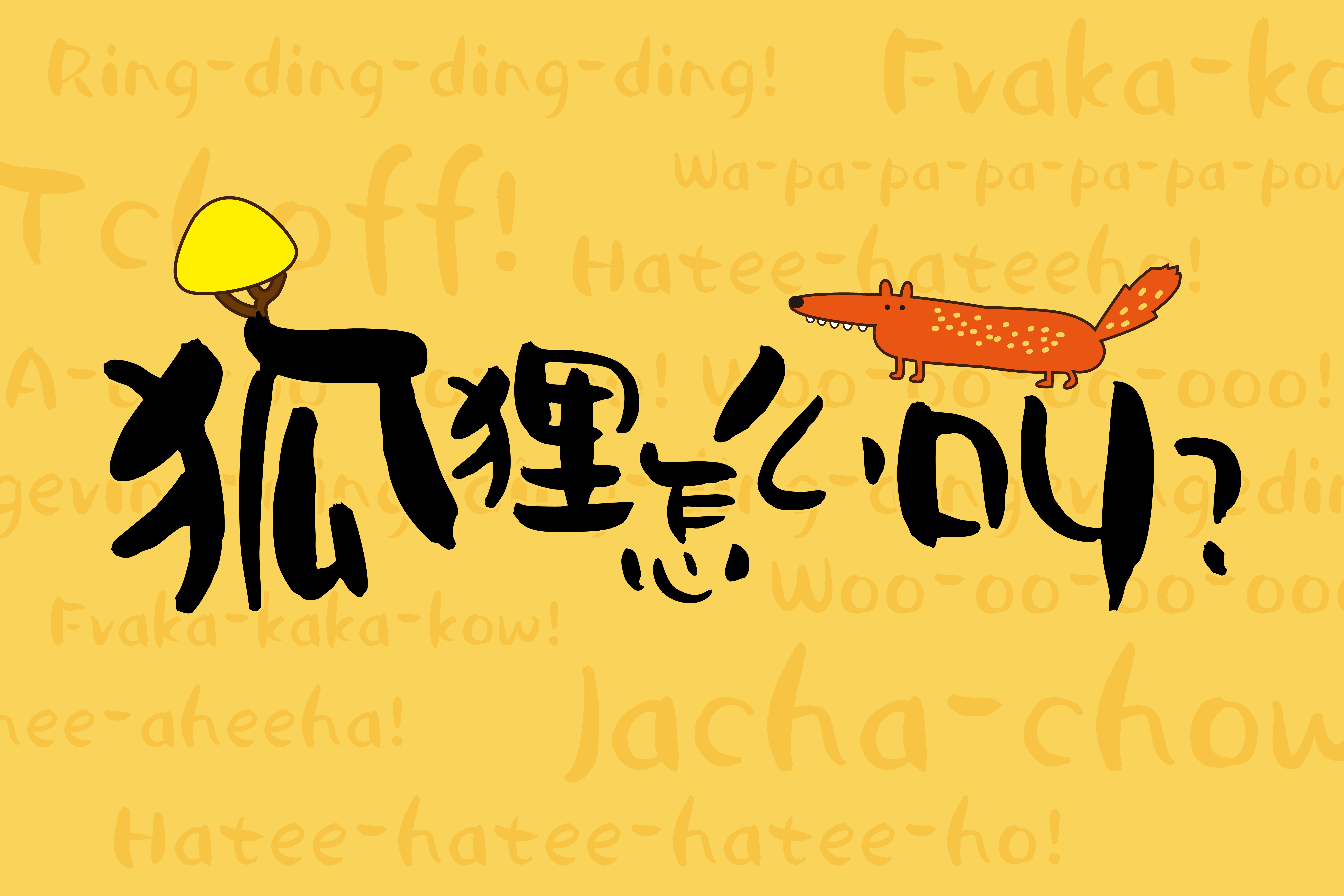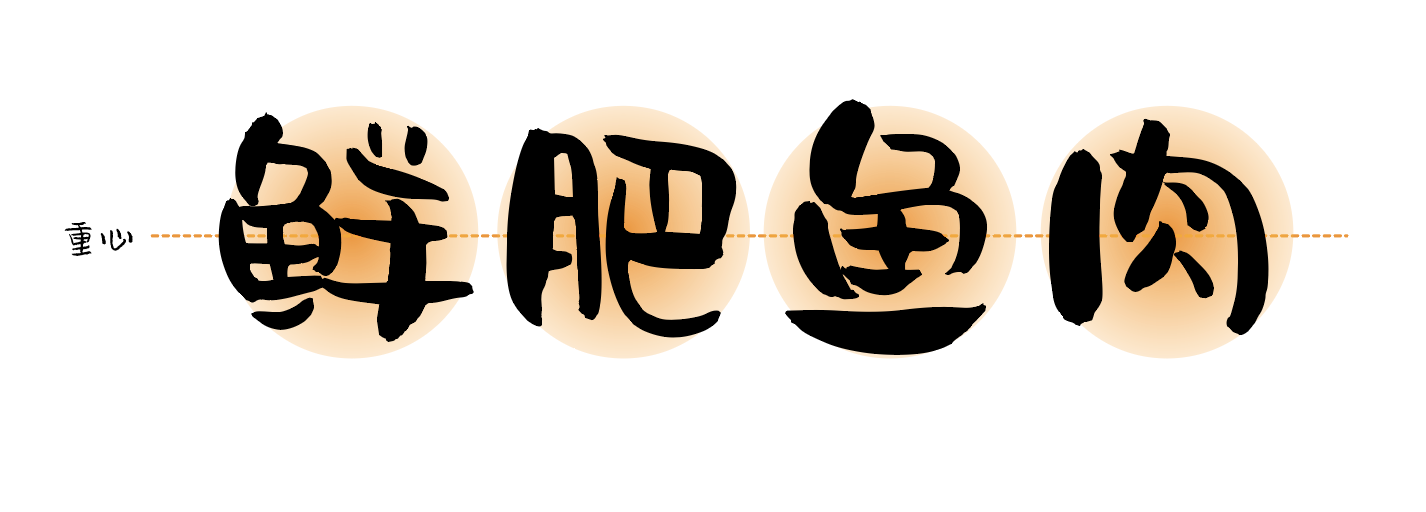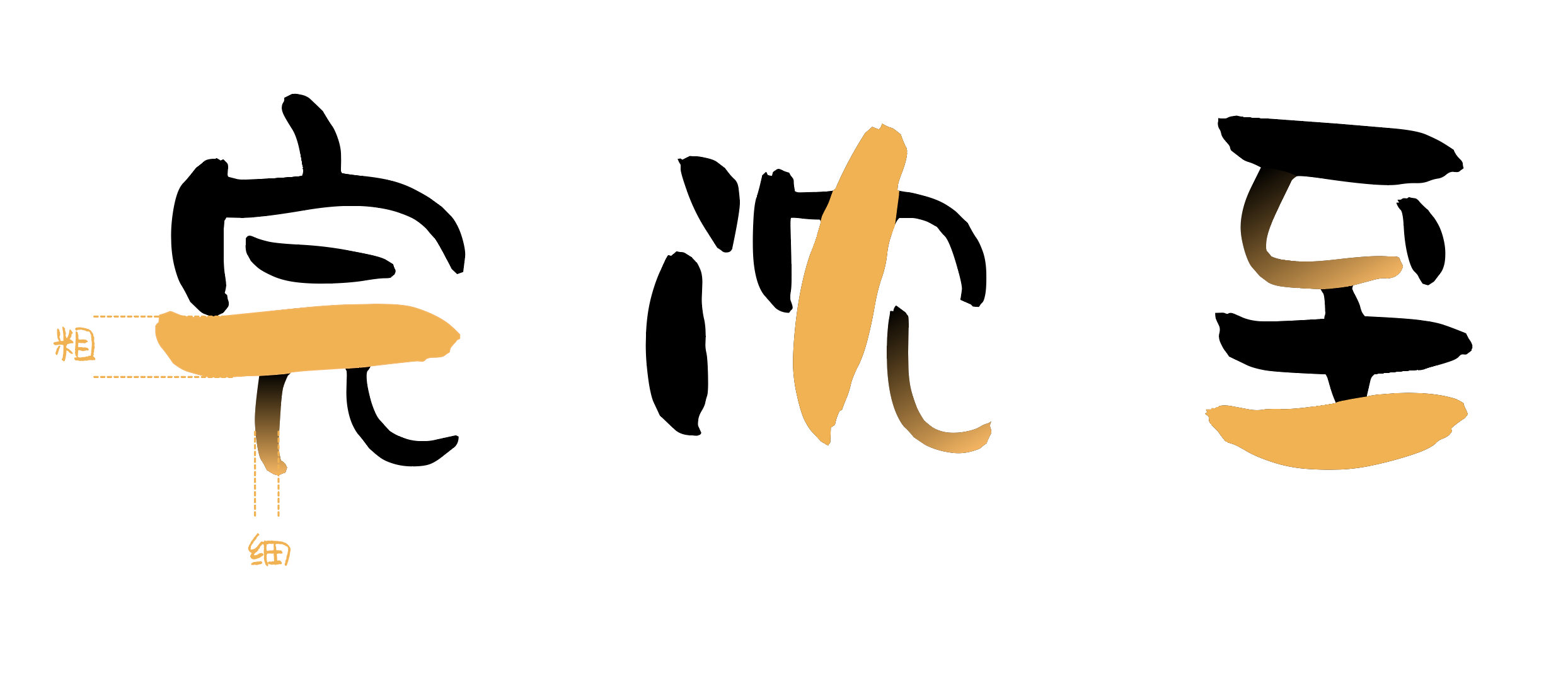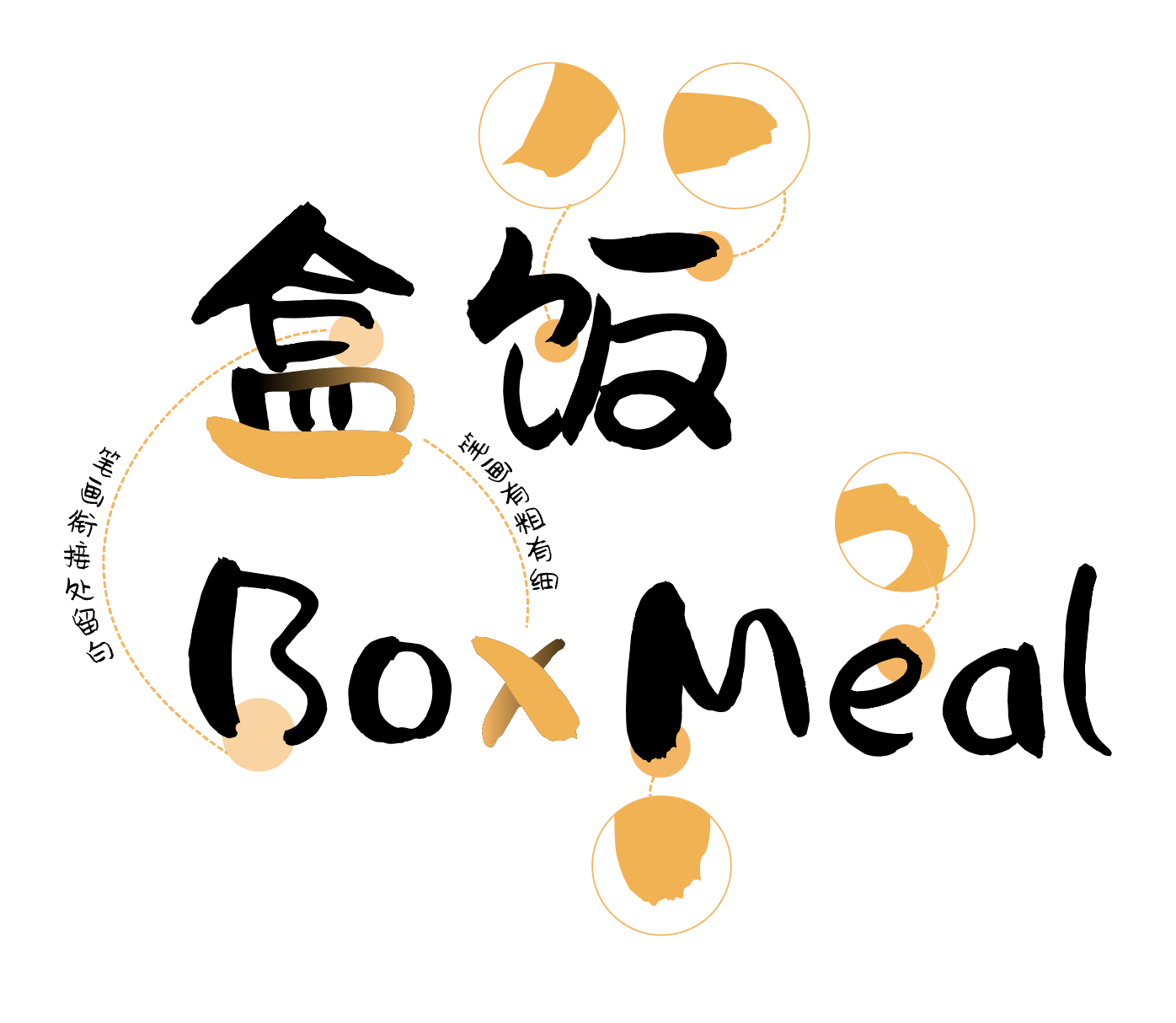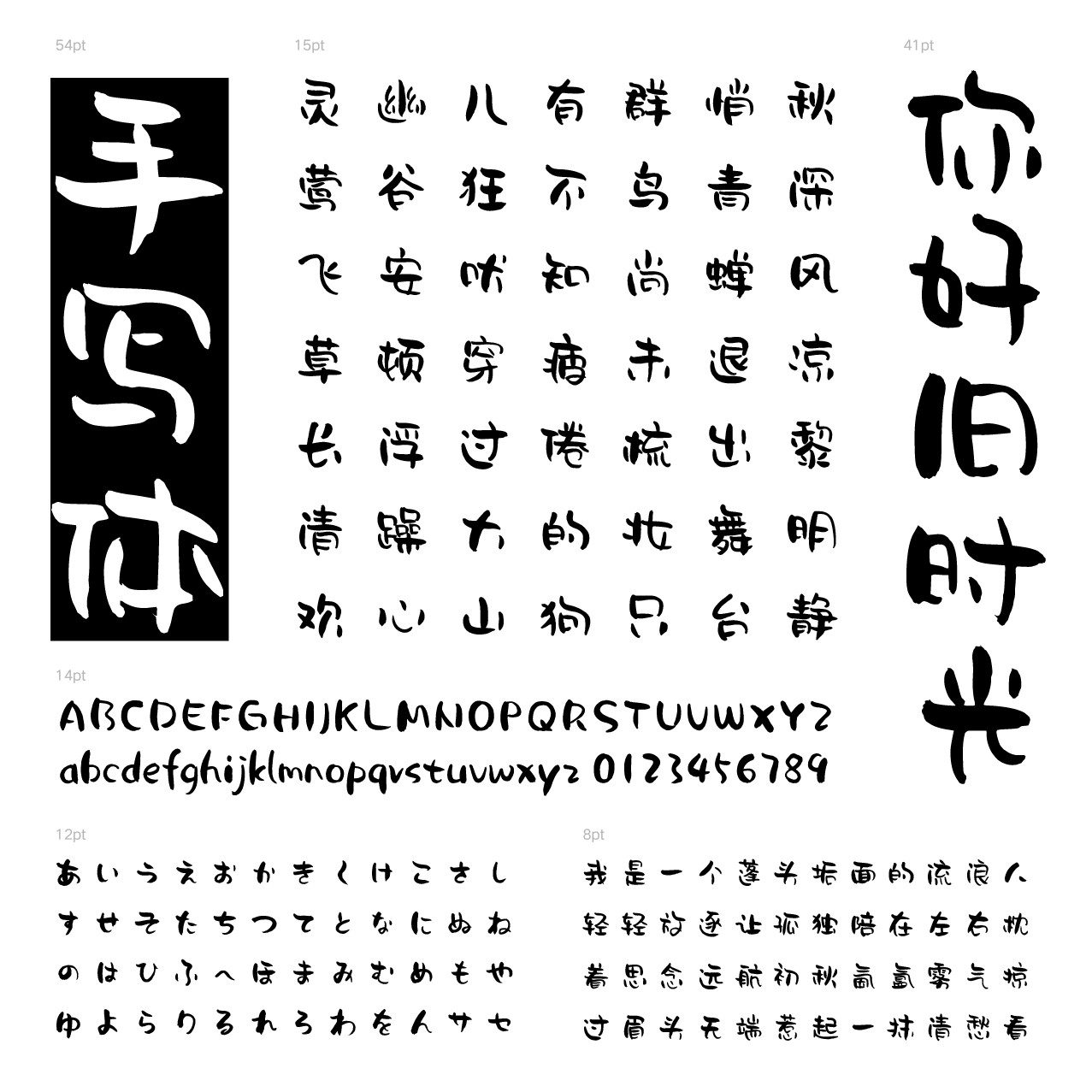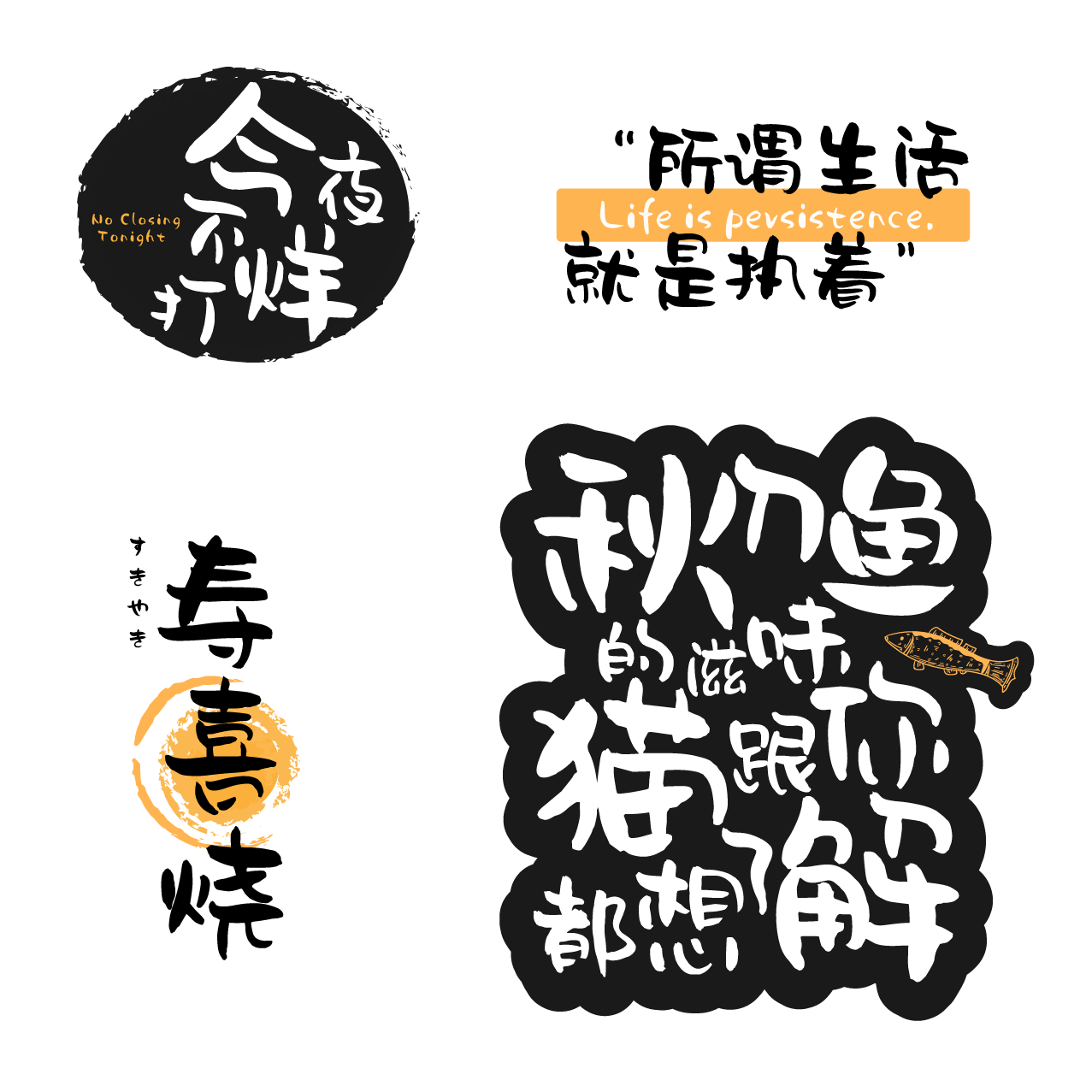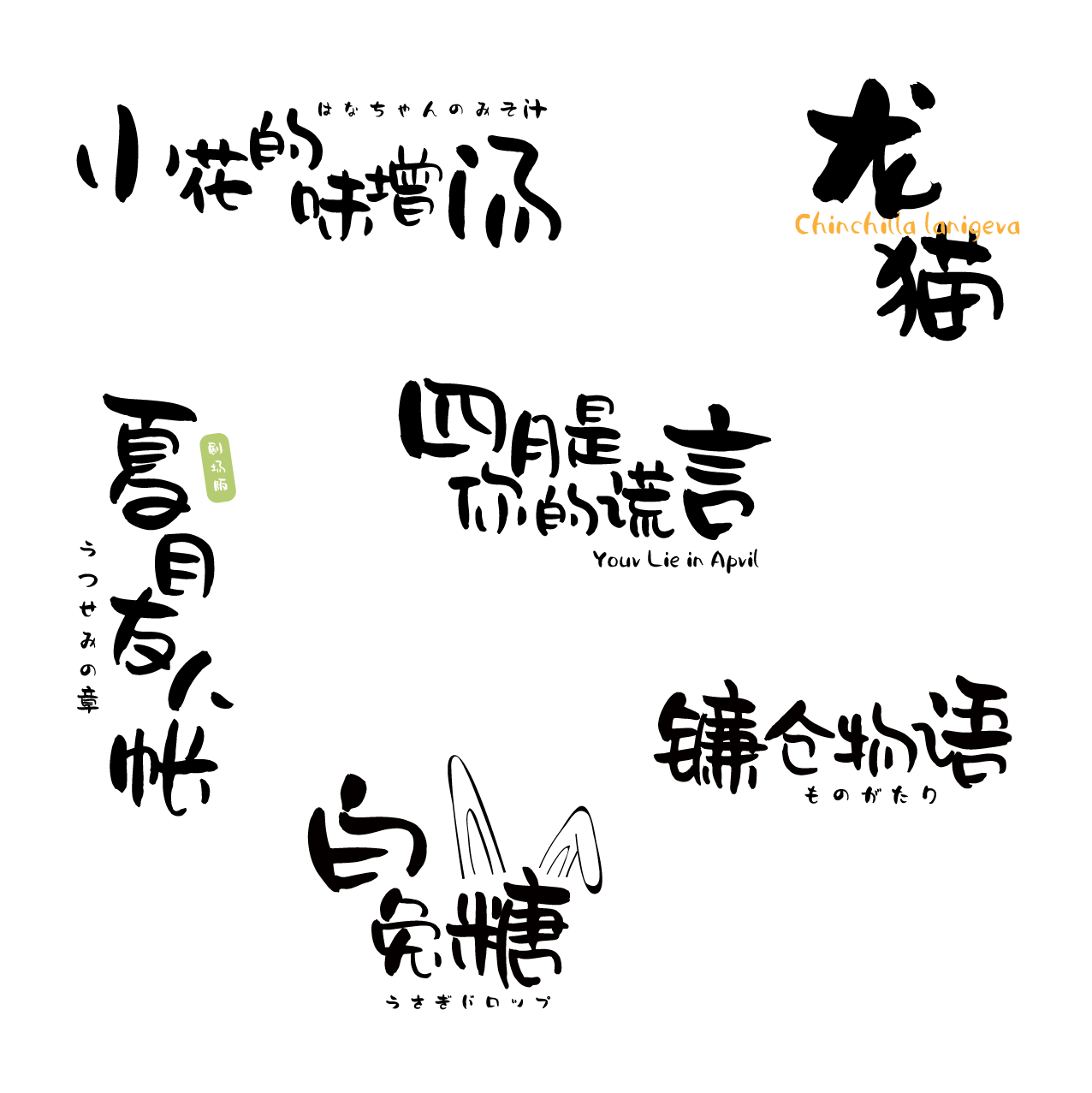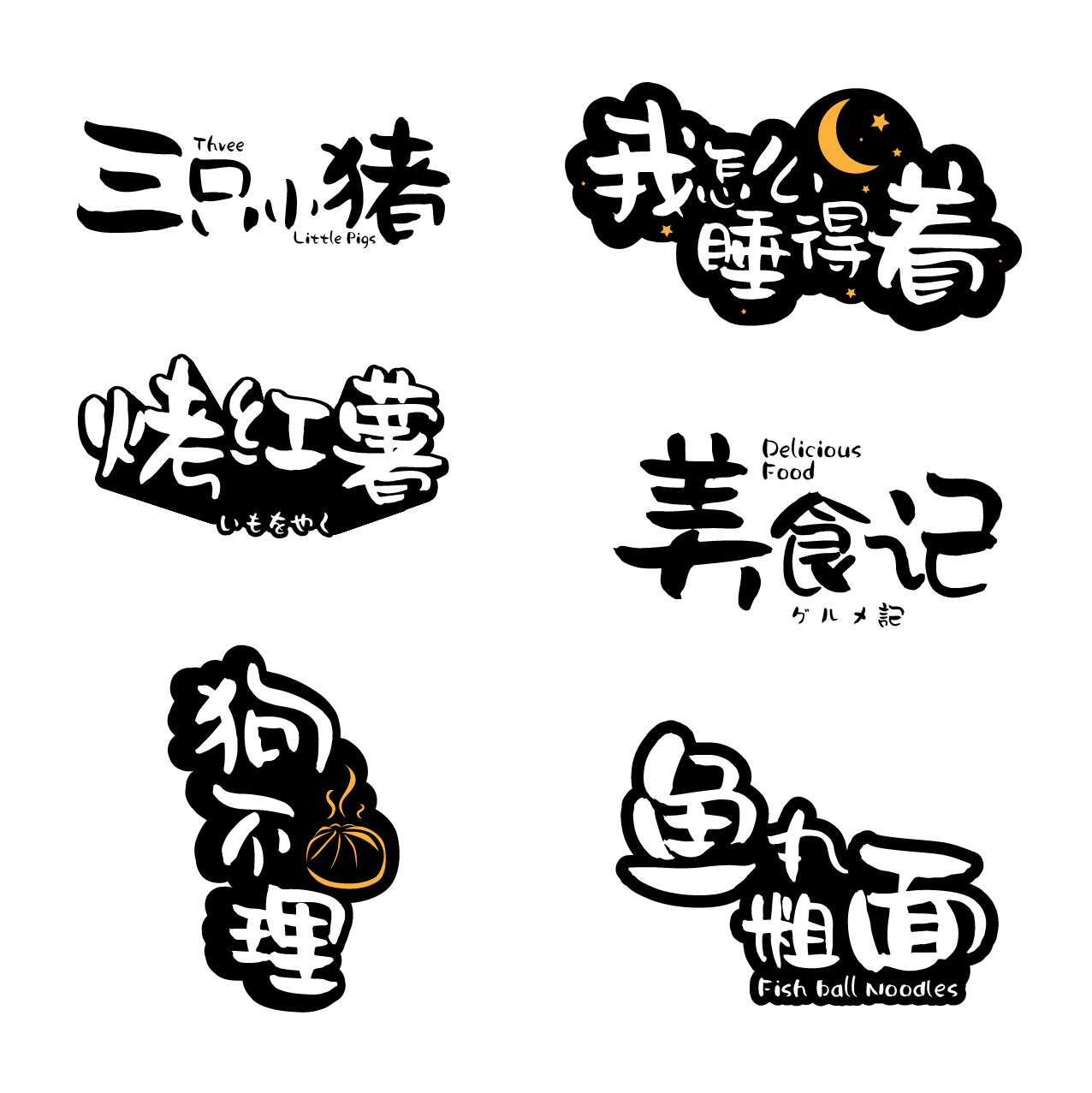
汉仪尚巍自由字体介绍,一款自由随性的手写字体
手书
可爱 / 随性 / 轻松 / 温暖 / 活泼
标志 / 广告 / 游戏 / 书籍排版 / 影视 / 包装
汉仪尚巍自由|自然随性
汉仪尚巍自由是由90后新锐字体设计师尚巍倾力打造的一款自由随性的手写字体。它的性格活泼调皮,结构灵动放松,连笔生动流畅,可以作为标题字被应用于产品包装、广告设计、logo、影视动漫等多种场景。
汉仪尚巍自由|设计特点
汉仪尚巍自由的字形偏圆。无论是左右结构还是上下结构的文字,都在保证识别度的基础上给予笔画不同程度的变形,自然洒脱的笔画让字体变得圆圆滚滚,有亲切感。
汉仪尚巍自由笔画的粗细变化十分明显,这是因为作者在书写时手法轻松舒缓,不受古板约束。
汉仪尚巍自由的笔画以圆润为主,连笔生动有趣,自然流畅,细节处均体现着字体的可爱。
汉仪尚巍自由|中西文匹配
汉仪尚巍自由的西文同样使用毛笔书写,形成了带有朴拙韵味、风格轻松愉悦、自由自在的字母。中西文搭配使用时和谐统一。
汉仪尚巍自由|排版效果